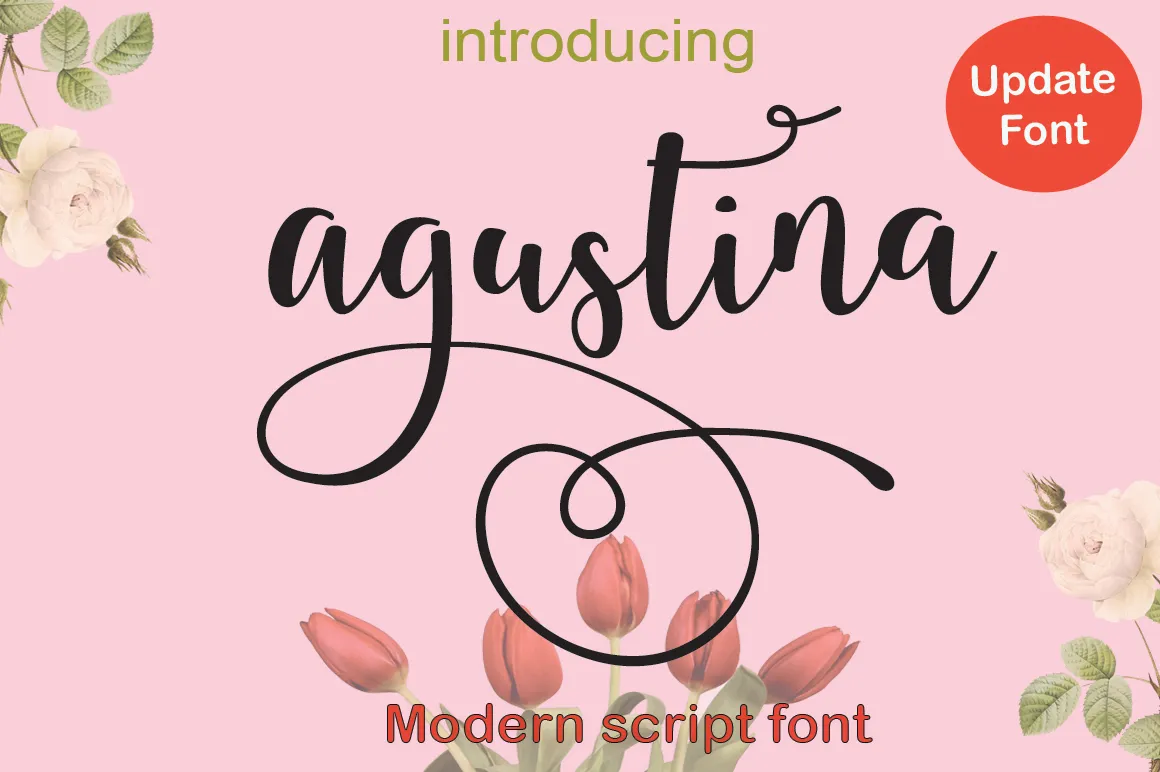
A Agustina Script Font é uma moderna escolha para qualquer projeto que deseje dar um toque sofisticado e elegante ao texto. Introduzida pelo designer Hamilton, a Agustina se tornou um ícone entre os tipos de script. Com seu traçado chamigráfico variando em baseline, oferece um toque clássico e envolvente que vai do uso em cabeçalhos aos selos de casamento e até mesmo nas etiquetas de embalagem. Perfeita para criar texturas interessantes em diversos formatos de materiais gráficos como cartazes, assinaturas e badais. Essa font é adaptável para uma ampla gama de aplicativos gráficos, tornando-a perfeita para os mais variados projetos. É ideal tanto para o design dos selos de casamento quanto para a criação de identidade visual, como cabeçalhos de websites ou publicações impressas. Além disso, é uma ótima opção para quem busca um estilo elegante e moderno para suas próximas criações gráficas. Com a Agustina Script Font, você pode garantir texturas impecáveis em sua próxima produção visual.